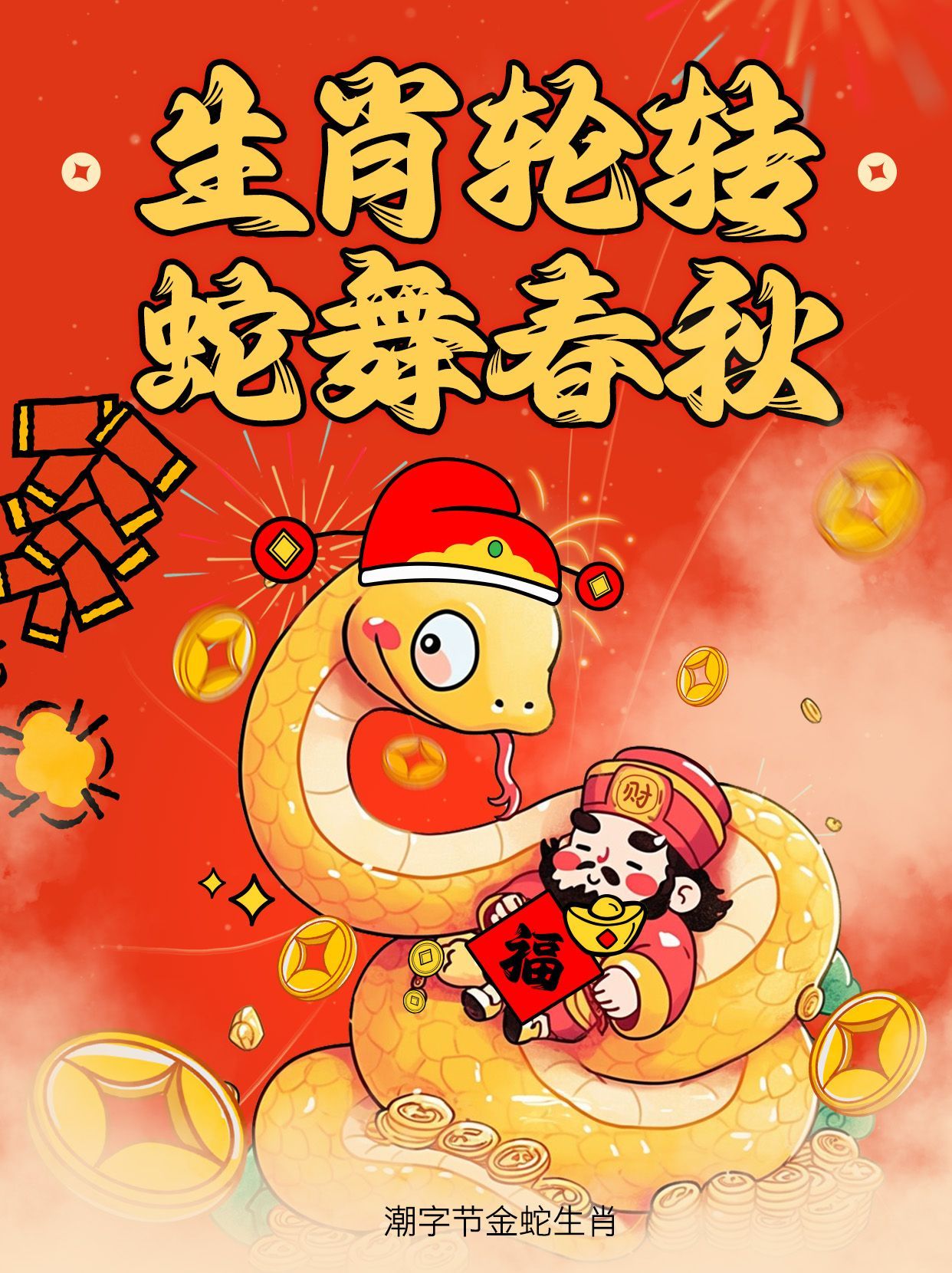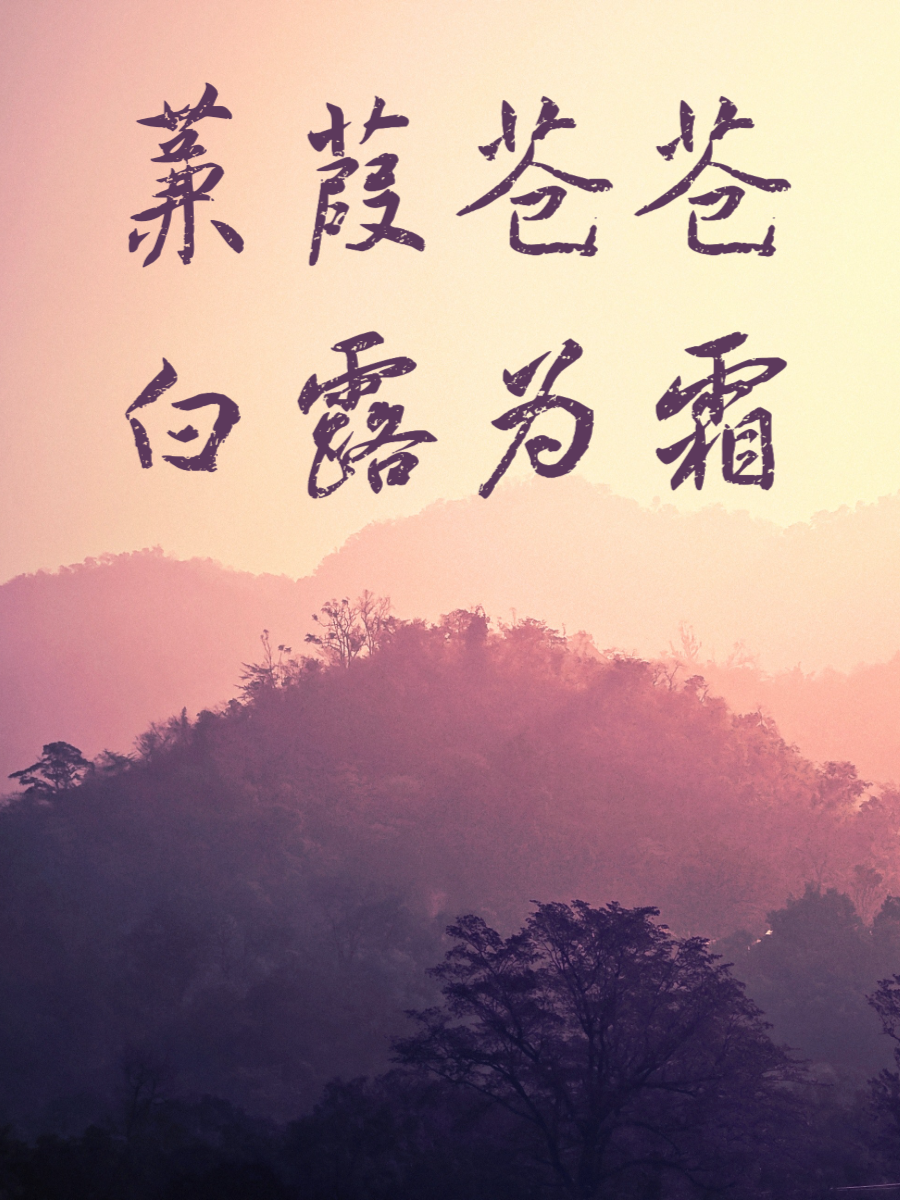
🌸 1. 【汉字之美三行归隐简】 → 洒脱情书天花板!💌
「复古天花板书法!优雅书法搭配烫金效果」
🎨 场景:手写诗句卡片、复古婚纱照排版
💬 文案参考:“初见乍惊欢,久处亦怦然”
🖋 2. 【龙书法杨永志瘦金行楷体】 → 宫廷美学暴击!👑
「帝王级书法字体!笔锋如刀自带清冷贵气」
🎨 场景:定制竹简情书、汉服写真题词
💬 文案参考:“山河远阔,人间烟火,无一不是你”
🎨 3. 【潮字节·金蛇生肖体】 → 元宇宙国风玩家必备!🐍
「蛇形笔画+流光特效,动态海报秒杀全场」
🎨 场景:AR告白视频、电子请柬动态标题
💬 文案参考:“缠绕你心,岁岁年年”
▸ 搭配技巧:霞飞路宋体做主标题 + 瘦金体做诗句点缀 → 古风叠buff!